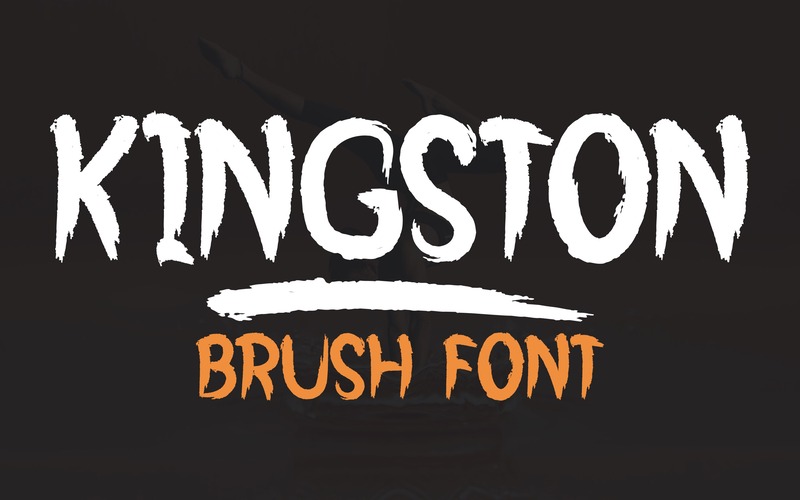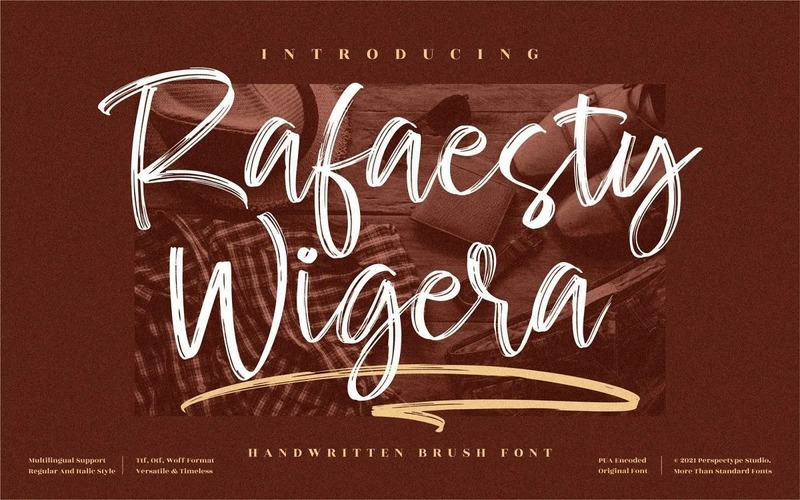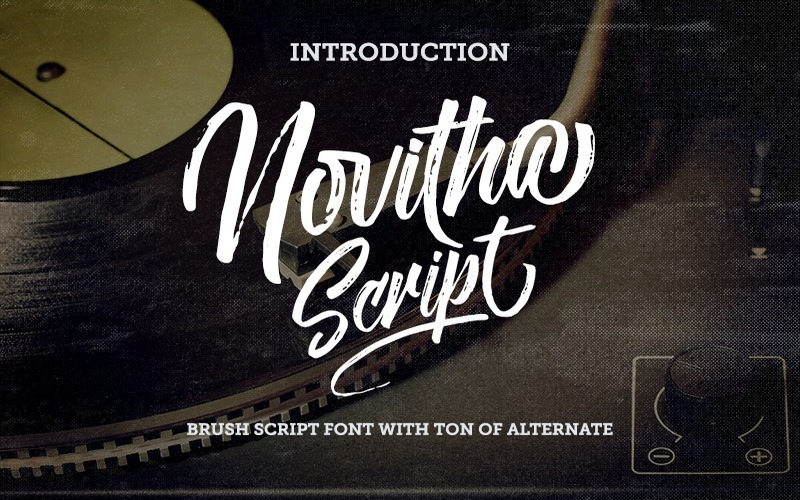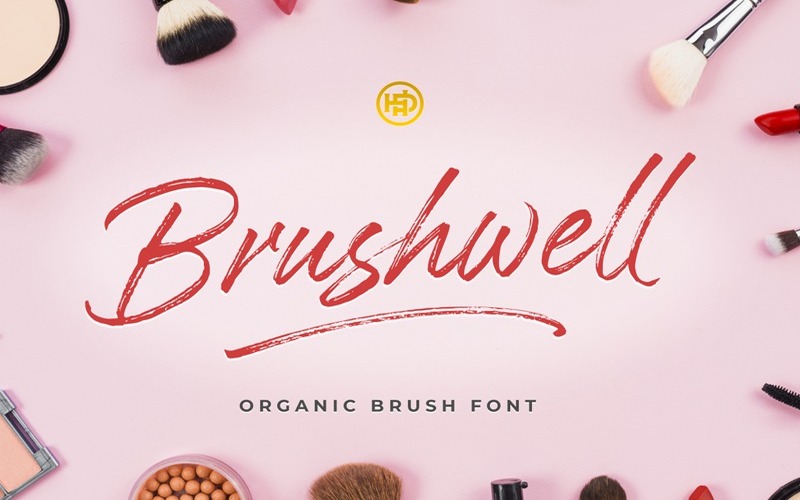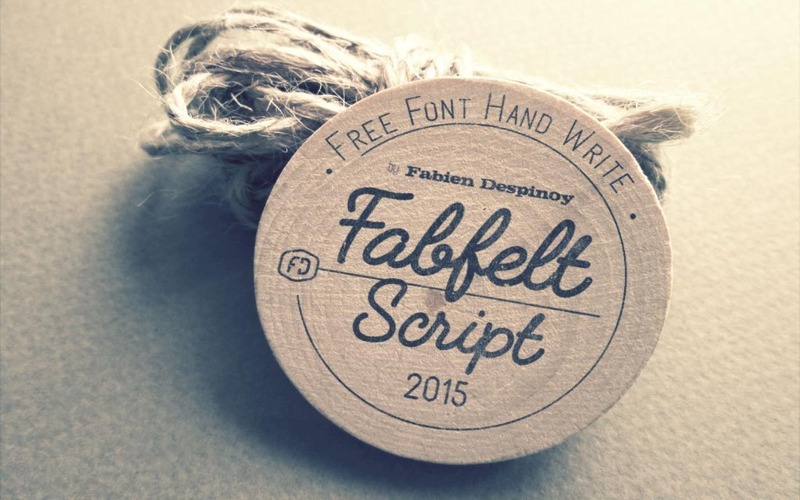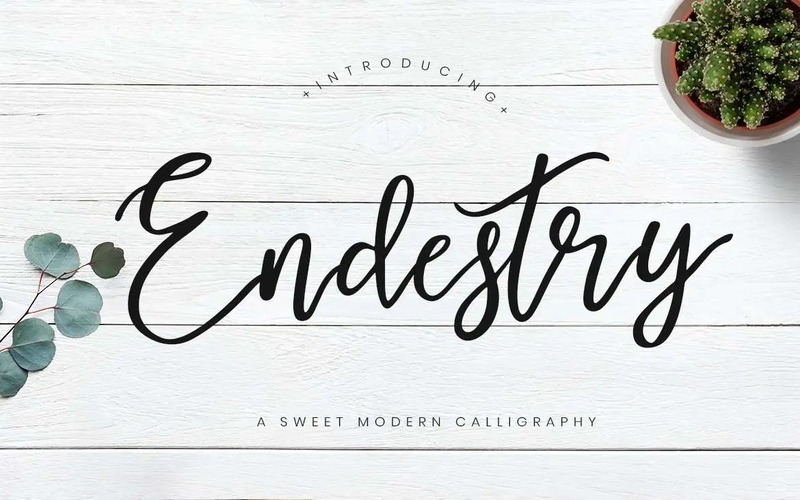
Tổng hợp 13 Font Brush Việt hóa đẹp
Một số font chữ Việt hóa hiện đang thu hút sự chú ý lớn từ các designer mới vào nghề. Sự đa dạng và biến hóa trong kiểu dáng cùng nội dung của chúng tạo nên sức hấp dẫn nổi bật với người xem. Đặc biệt, font chữ Brush Việt hóa được các chuyên gia thiết kế nội dung, logo và in ấn đánh giá rất cao nhờ phong cách độc đáo và linh hoạt trong sử dụng.
Giới thiệu đôi nét về Font Brush
Font Brush tiếng Việt là một loại font chữ được việt hóa, lấy cảm hứng từ những nét chữ viết tay tự nhiên và mềm mại, được thiết kế dưới dạng vector để dễ dàng sử dụng trên máy tính. Đây là một công cụ quan trọng trong lĩnh vực thiết kế sáng tạo, được ứng dụng rộng rãi không chỉ trên thế giới mà cả tại Việt Nam. Việc việt hóa Font Brush giúp các nhà thiết kế có thêm nhiều lựa chọn font chữ độc đáo, phù hợp với đa dạng dự án, từ thiết kế logo, poster, đến các ấn phẩm quảng cáo, mang lại sự sống động và cá tính cho sản phẩm cuối cùng.
Tồng hợp Font chữ Brush việt hóa
Kingston Font
Kingston là font chữ viết tay độc đáo với những đường nét vẽ hoa tinh xảo, mang lại vẻ đẹp sang trọng cho sản phẩm. Font phù hợp cho thiết kế logo, thiệp mời, tờ rơi, áo thun, bảng hiệu, áp phích, poster, huy hiệu và nhiều ứng dụng khác.
Rafaesty Wigera Font
Rafaesty Wigera có nét chữ tự do, không đối xứng, phản ánh sự sáng tạo và cá tính mạnh mẽ. Đây là lựa chọn hoàn hảo cho các dự án đòi hỏi phong cách cá nhân, khác biệt.
Novitha Script Font
Novitha Script là font brush tiếng Việt được phát triển từ Novitha Script của Lostvoltype Typeface, nổi bật với những đường nét cọ viết tay đặc trưng, giúp tác phẩm của bạn trở nên nổi bật và ấn tượng hơn.
Bougher Font
Bougher là font chữ viết tay mang phong cách cổ điển, với hai phiên bản chữ thường và chữ nén, mỗi ký tự có biến thể riêng. Phù hợp cho các dự án thiết kế sáng tạo đậm chất vintage.
Brushwell Font
Brushwell Brush là font chữ cọ vẽ tự do, hoang dại với các đường nét mềm mại, tự nhiên. Font rất thích hợp cho việc cá nhân hóa thương hiệu, trang trí nội thất, bao bì sản phẩm hay các trích dẫn viết tay.
Fabfelt Script Font
Fabfelt Script do Despinoy Fabien thiết kế, được ưa chuộng trong các thiết kế mang phong cách hoàng gia, quý tộc. Phù hợp cho logo, poster cổ điển và các bài viết retro. Phiên bản Việt hóa giúp đơn giản hóa việc sử dụng trong các dự án tại Việt Nam.
Endestry Modern Calligraphy Font
Endestry là font calligraphy hiện đại việt hóa, lý tưởng cho thiệp mời, lời mời, thiết kế logo và các ấn phẩm quảng cáo. Font mang lại sự sang trọng, đẳng cấp, giúp làm nổi bật và chuyên nghiệp hóa sản phẩm thiết kế.
Font Brush việt hóa chính là công cụ đắc lực giúp các designer thể hiện sự sáng tạo, cá tính và tinh thần tự do trong từng nét chữ. Với sự đa dạng về kiểu dáng và phong cách, font Brush không chỉ làm nổi bật các thiết kế mà còn mang đến hơi thở nghệ thuật đầy cảm xúc, phù hợp cho nhiều lĩnh vực từ thiết kế logo, poster, thiệp mời đến in ấn thương hiệu. Nhờ khả năng việt hóa hoàn chỉnh, font Brush trở nên dễ dàng sử dụng và rất được ưa chuộng trong cộng đồng thiết kế Việt Nam, góp phần tạo nên những sản phẩm độc đáo, ấn tượng và chuyên nghiệp.